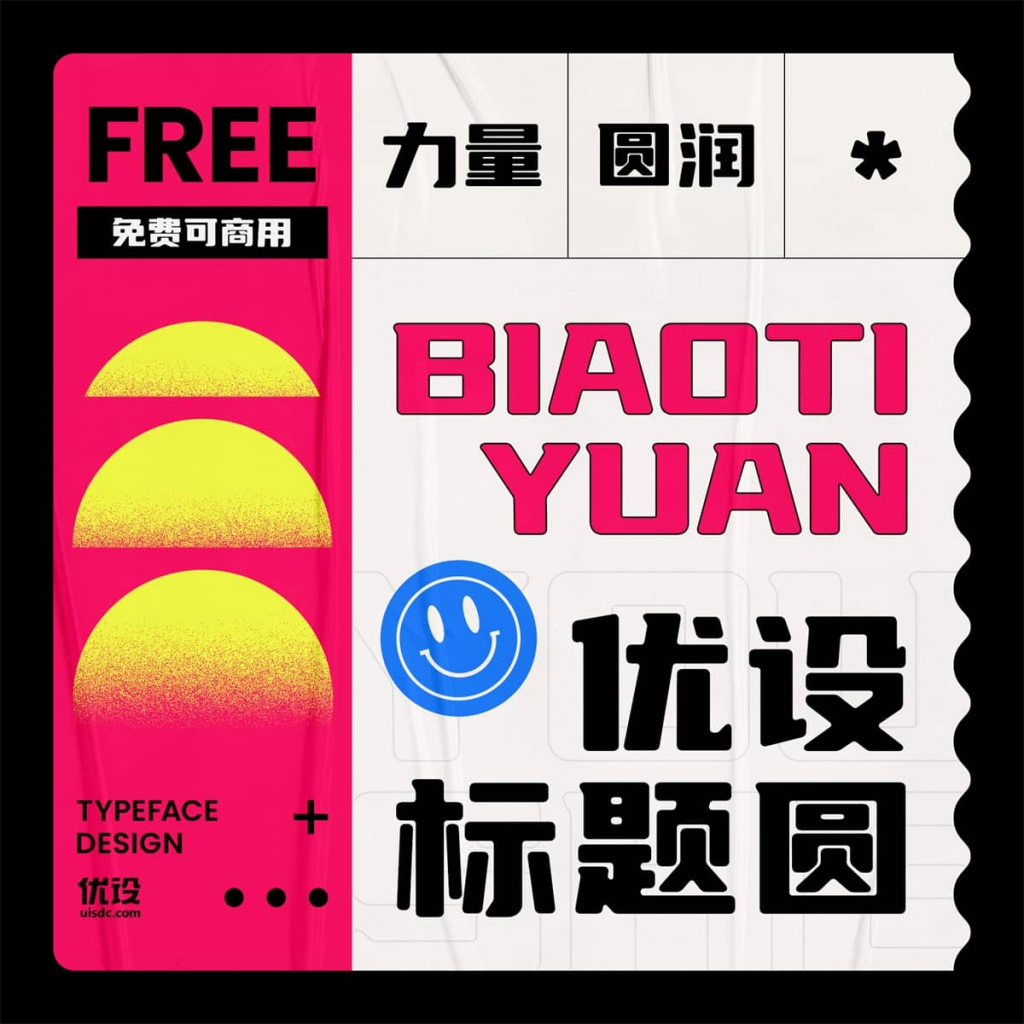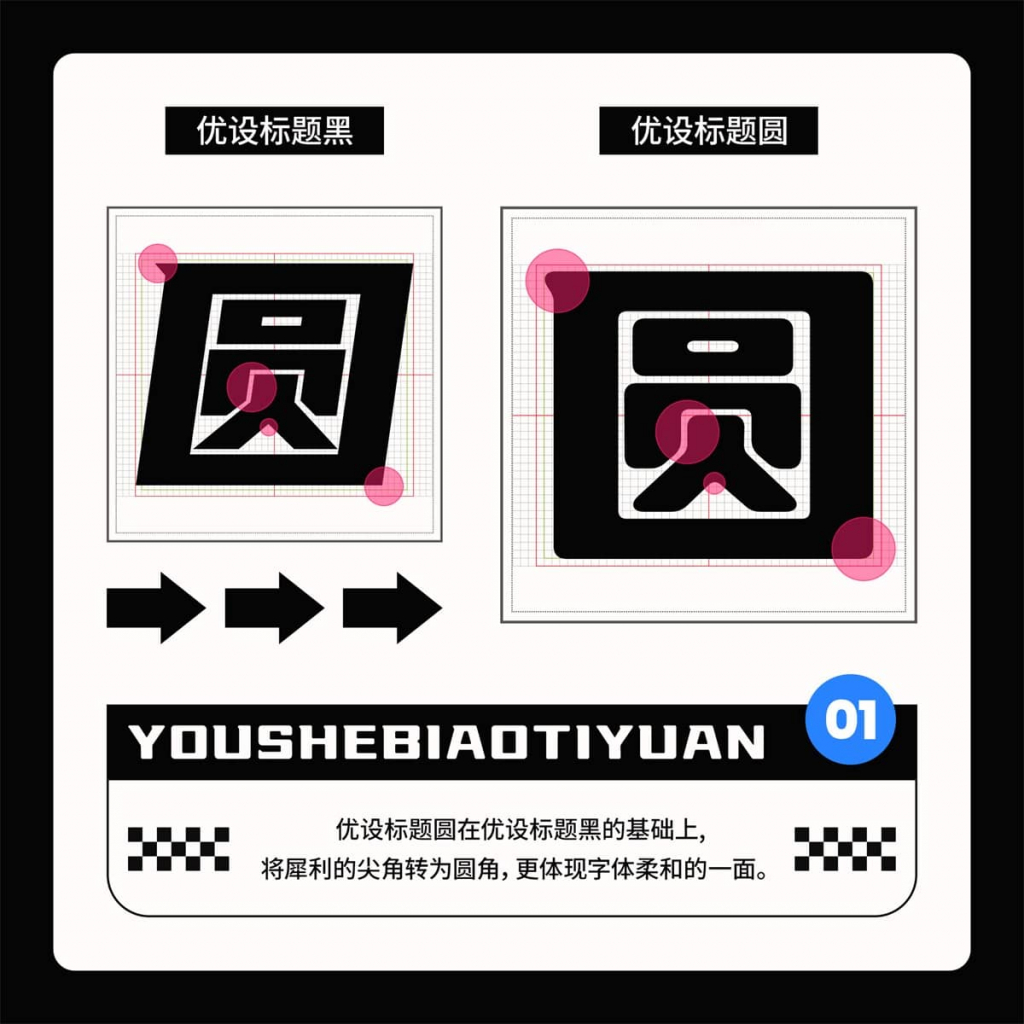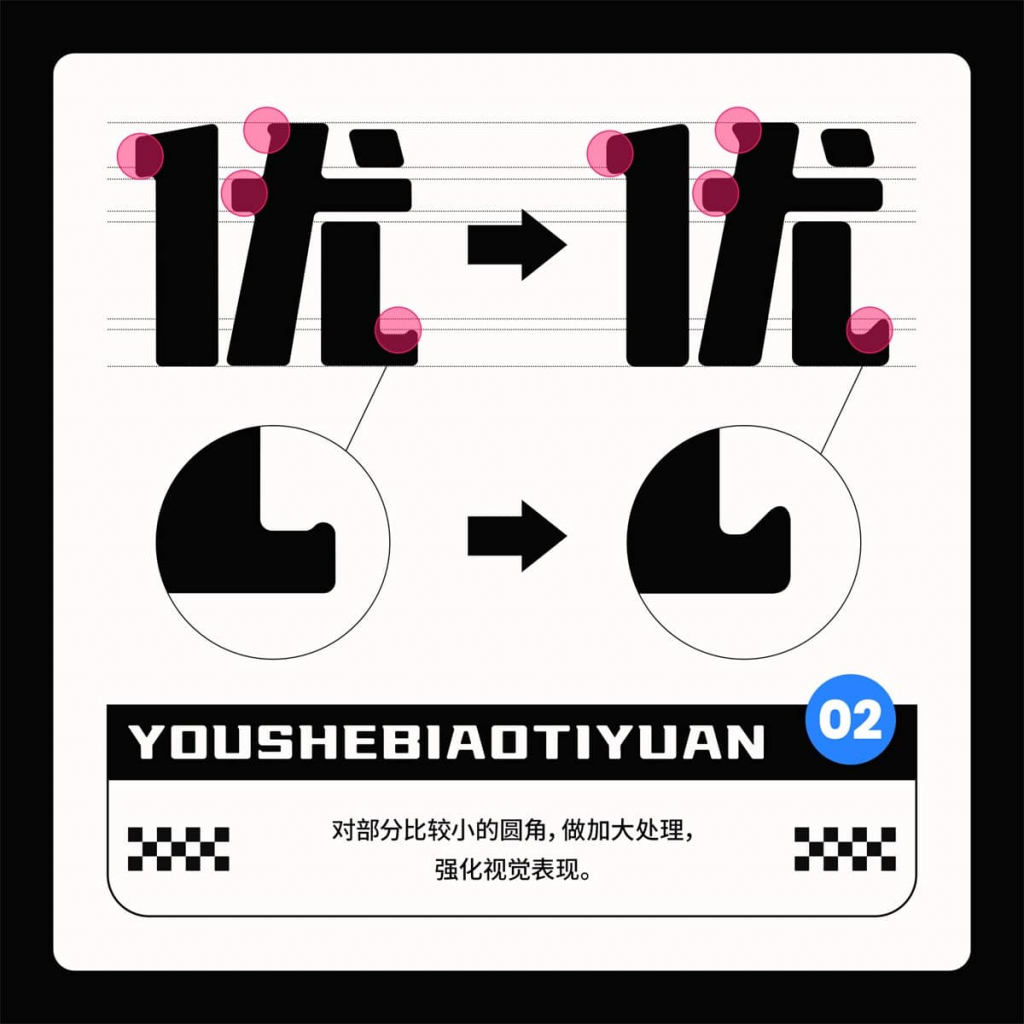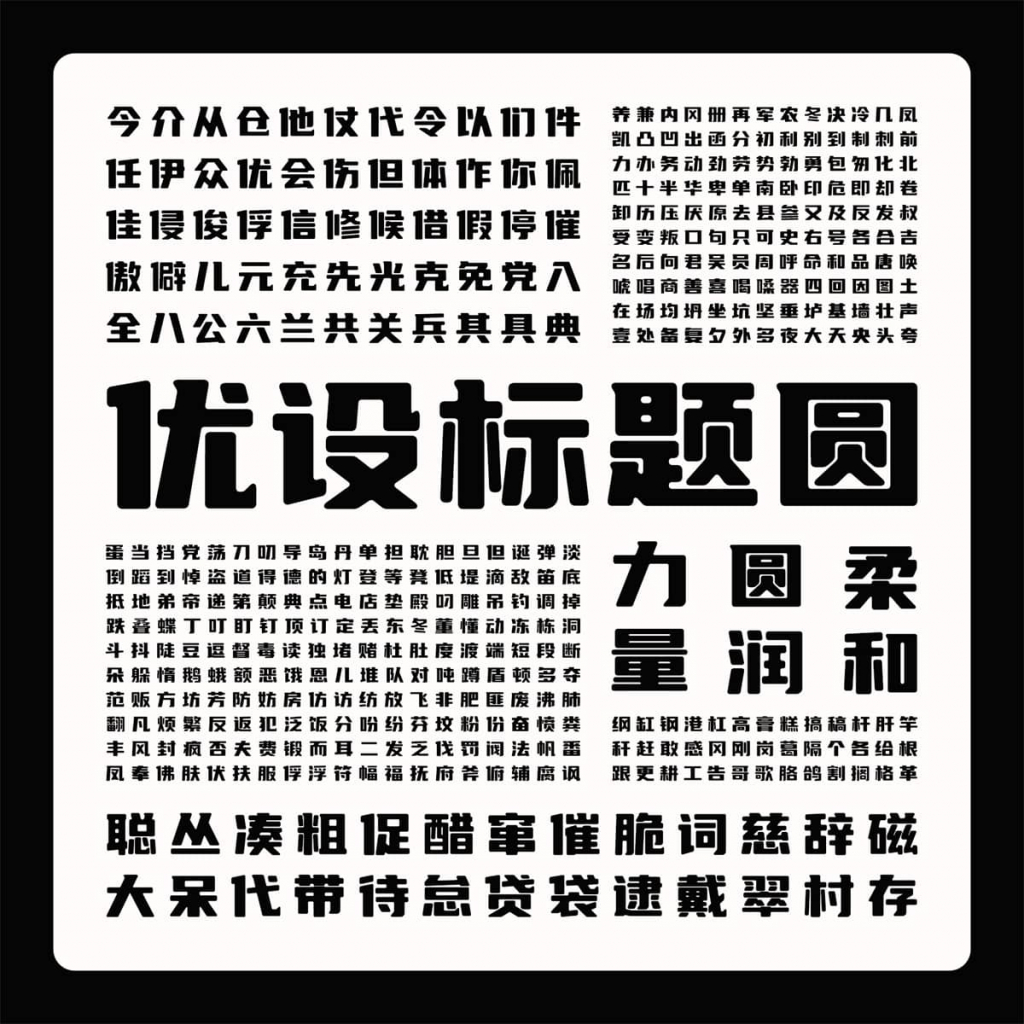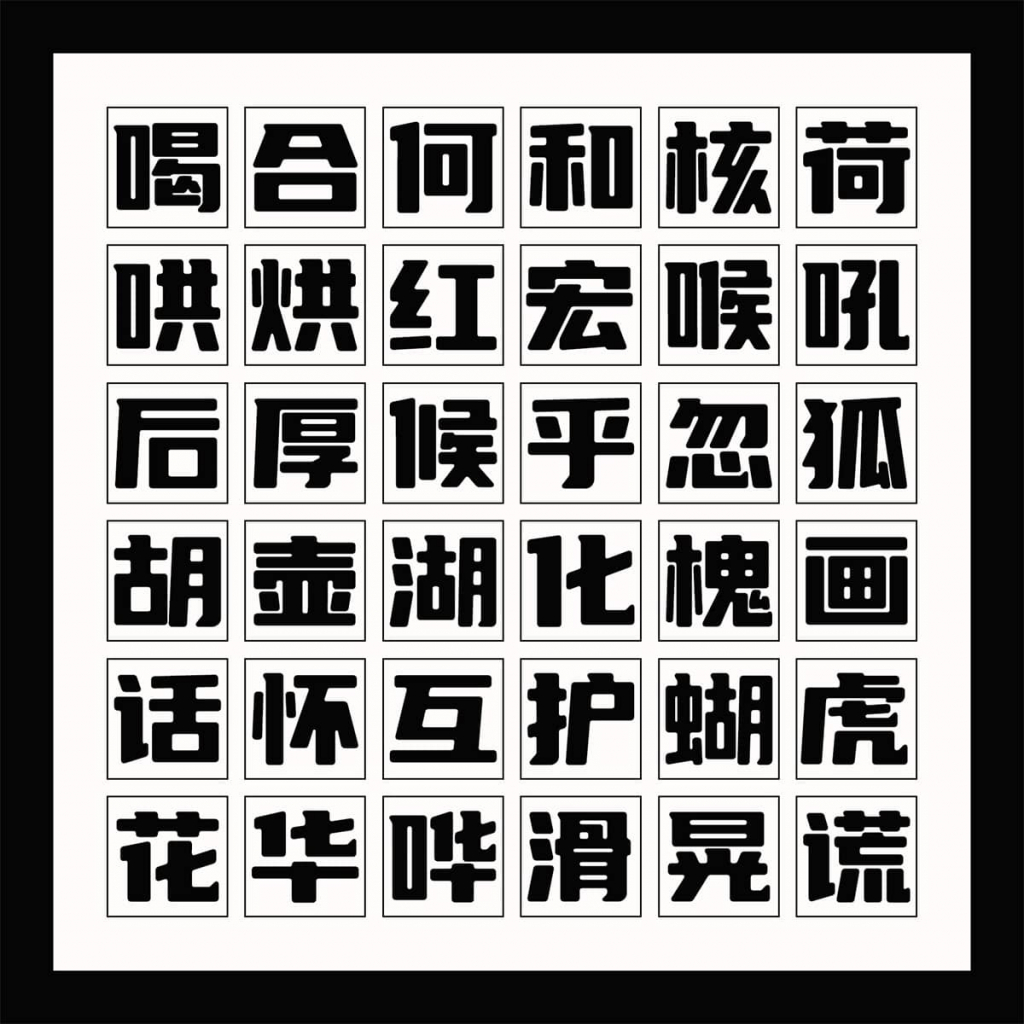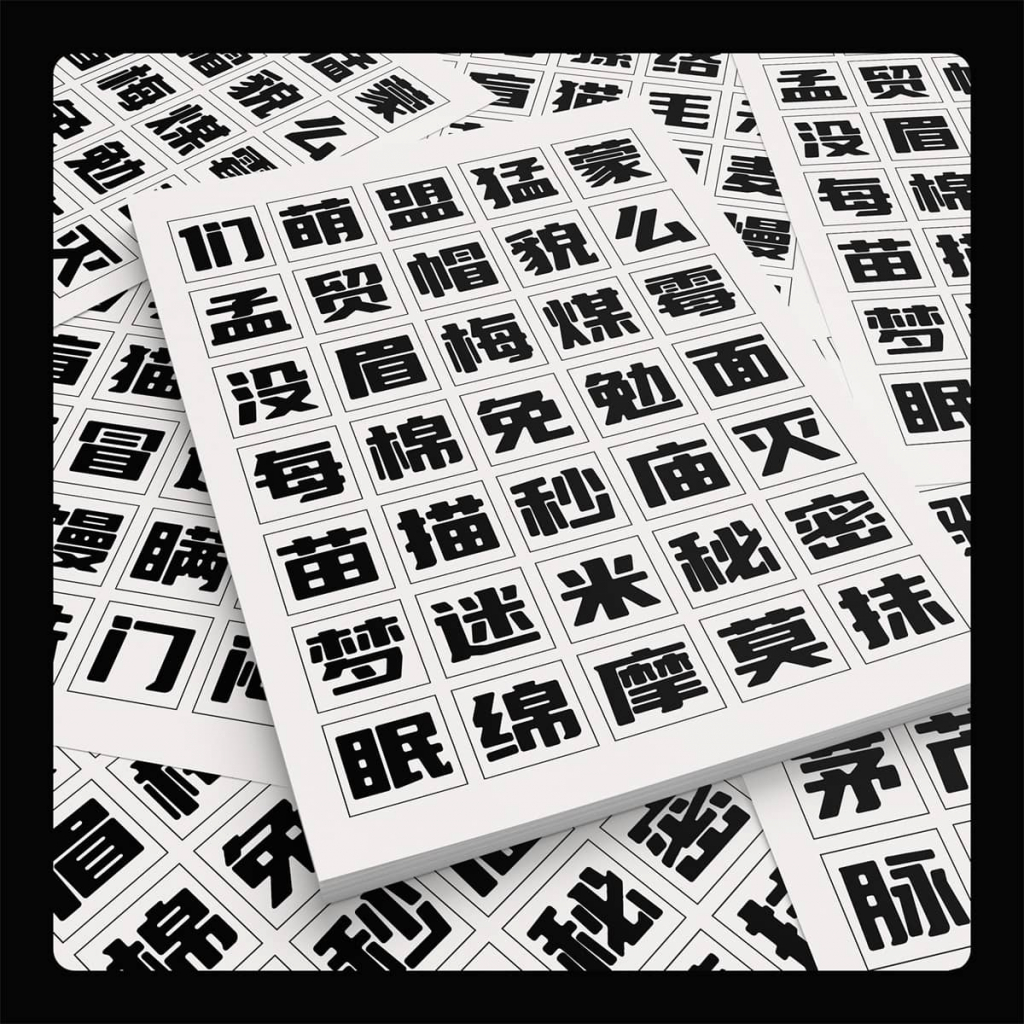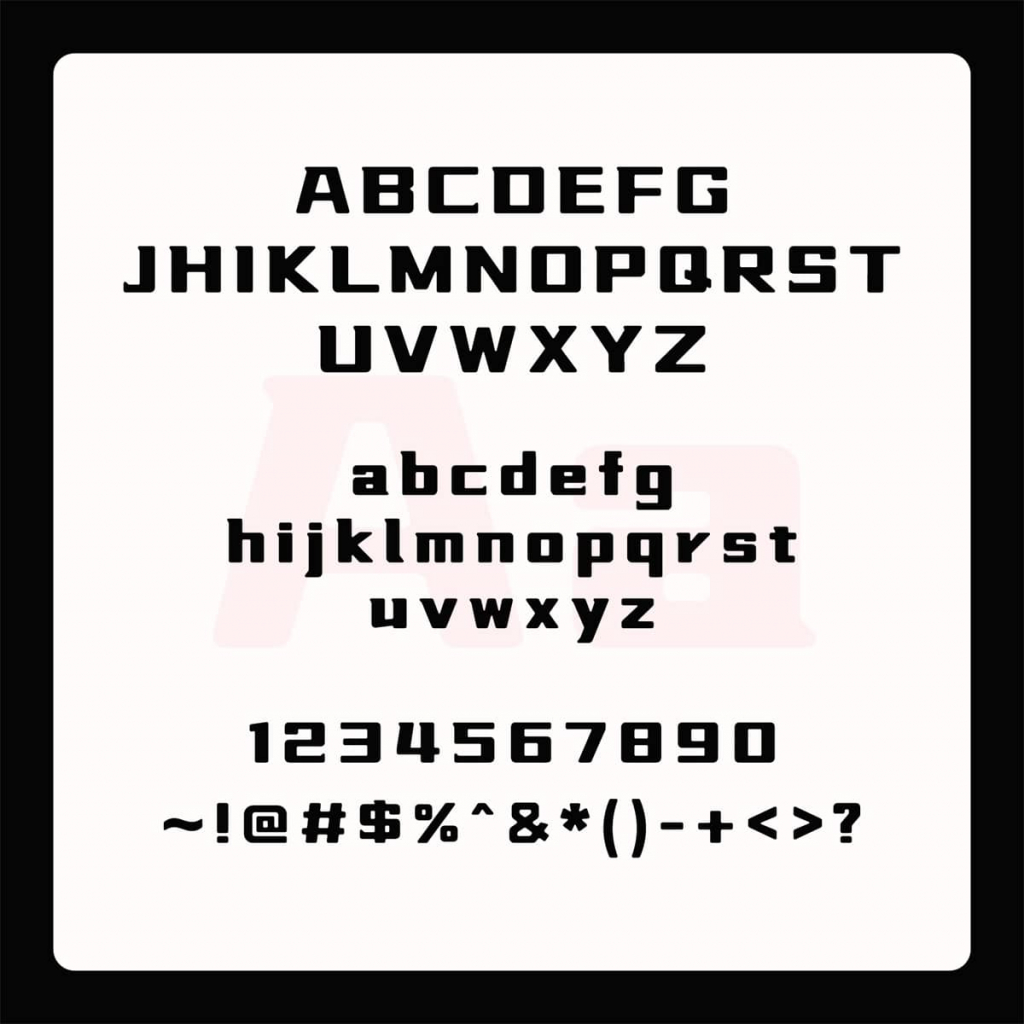
自「优设标题黑」发布以来,已经过去了两年多的时间。这款备受瞩目的字体在发布后,迅速风靡全国,成为了广受欢迎的国民级字体。而优设团队并未因此满足,他们集结了一支由中坚设计师组成的团队,继续发布了电商领域的两款新字体:「优设好身体」和另一款风格可爱的「优设字由棒棒体」。
令人感到欣慰的是,这两年来,无论是在各大电商平台、综艺节目、电影电视剧中,还是许多官方媒体上,都能看到我们这些字体的身影。特别是「优设标题黑」,它凭借其独特的速度感和力量感,赢得了众多设计师的喜爱。
但这两年我们也观察到一个现象:大家在使用标题黑时,可能会考虑将它调正进行使用,多方调研和讨论后,我们决定在「优设标题黑」的基础上做一个全新的版本,让它的使用范围更加广泛。历经一年多的修改后,这款标题黑的升级版,也是优设第4款免费可商用的中文字体:优设标题园上线啦!
作为「优设标题黑」的兄弟版,这款字体在保留「优设标题黑」的力量感的基础上,将8°倾斜去除,从斜体变为正体,减弱速度感,增加稳固的感受:
字体整体风格与标题黑形成直接对比,一个刚毅,一个柔和。
作为2022年首款送给设计师的礼物,也作为优设标题黑的升级版,我们不仅希望能见证另一款国民级字体的诞生,更希望越来越多设计师通过优设的字体,省下更多的时间,去拥抱休闲生活。